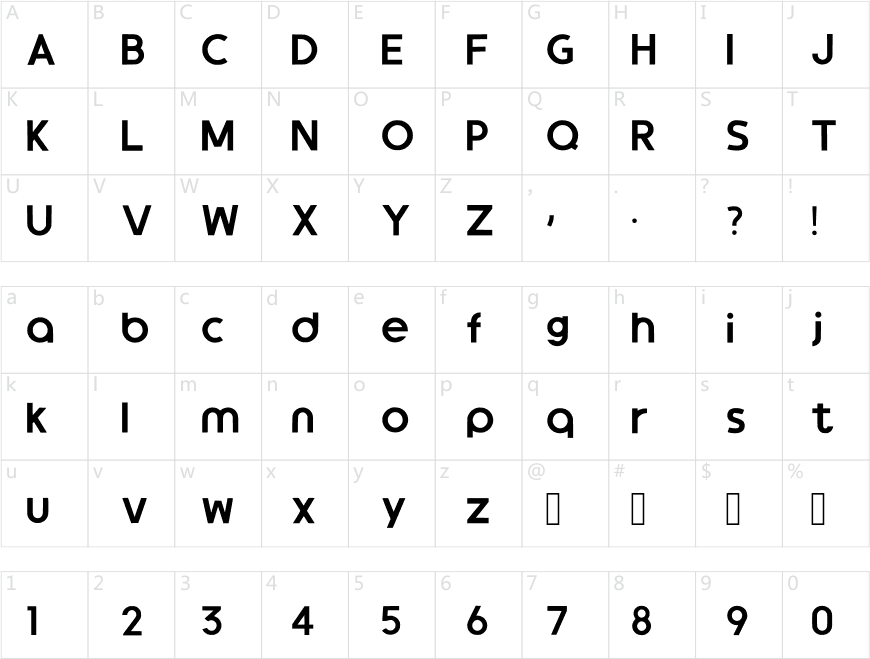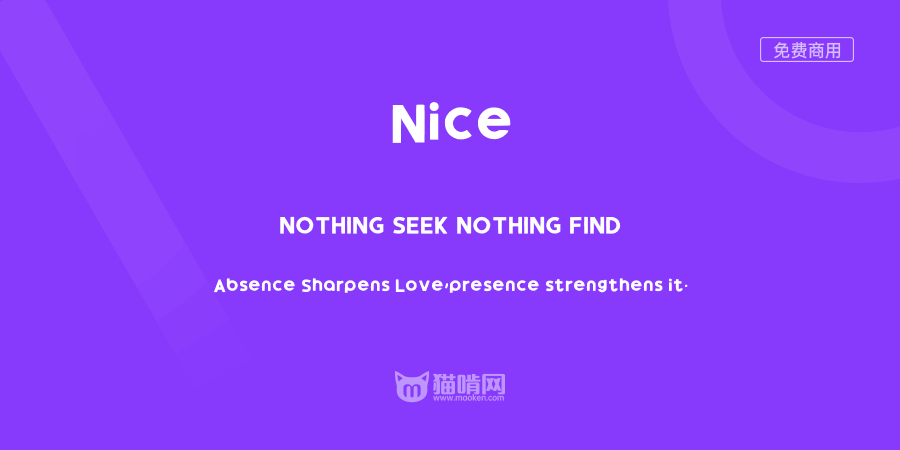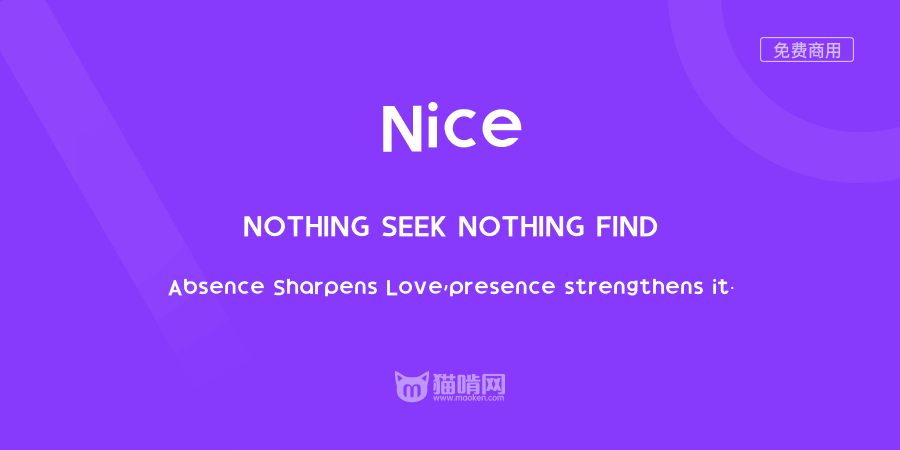
Nice
字体介绍:这是一款无衬线西文字体,是19年参加方正字体大赛的作品,虽未能获奖,但个人觉得这款字作为标题来使用是非常不错的,一直想做成字库,只怪自己太拖啦,一直到现在才整理出来,免费供各位使用。
生成字库后小写有一点小Bug,对齐稍微有点小问题,不过影响不大,大写比较完整,
作为标题使用是非常不错的。